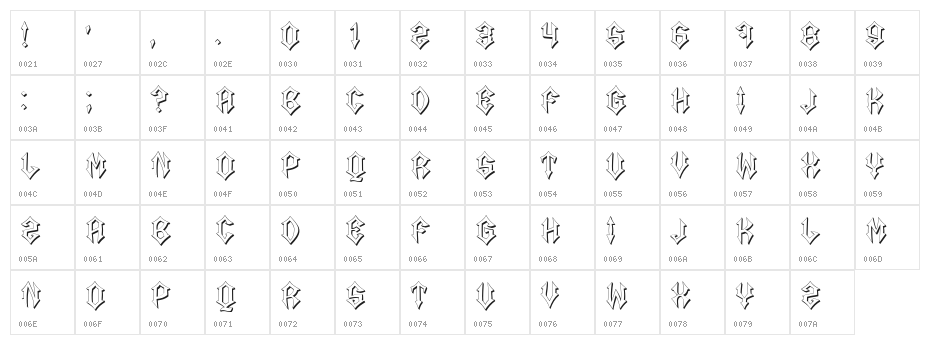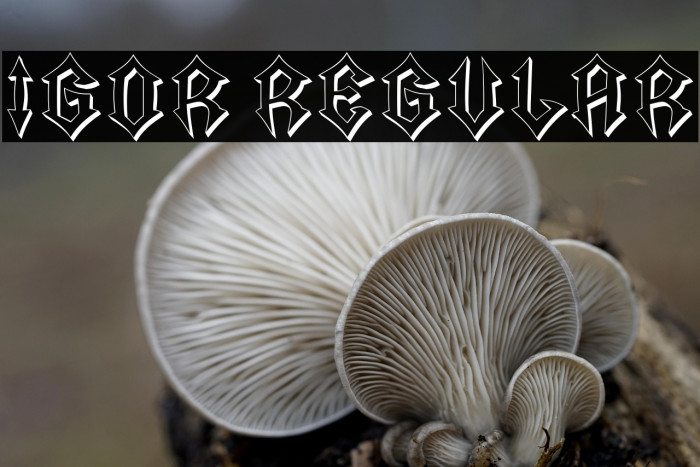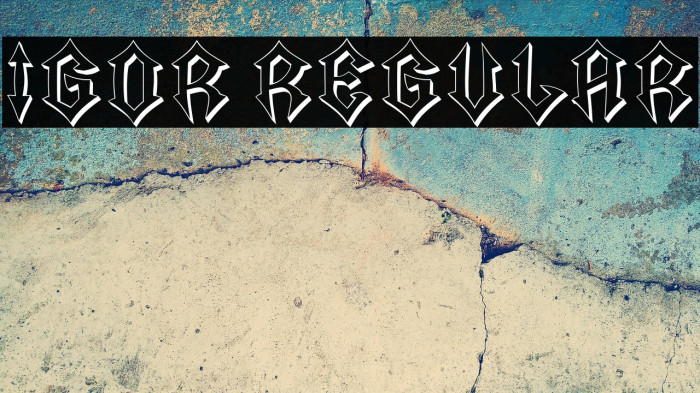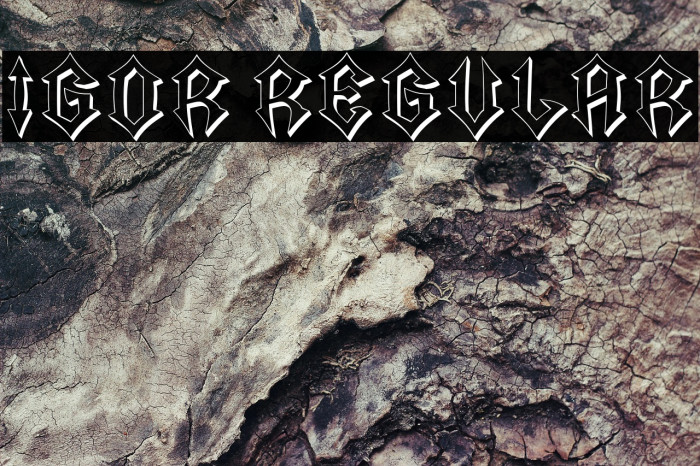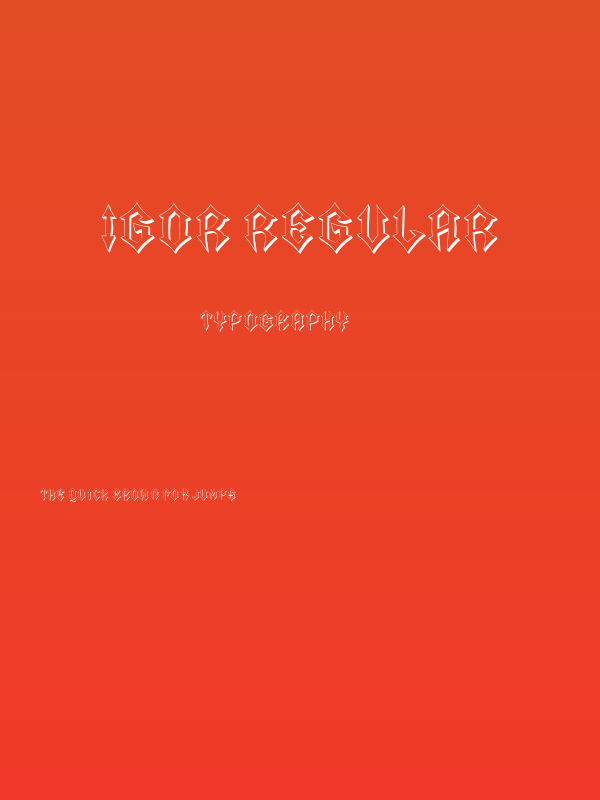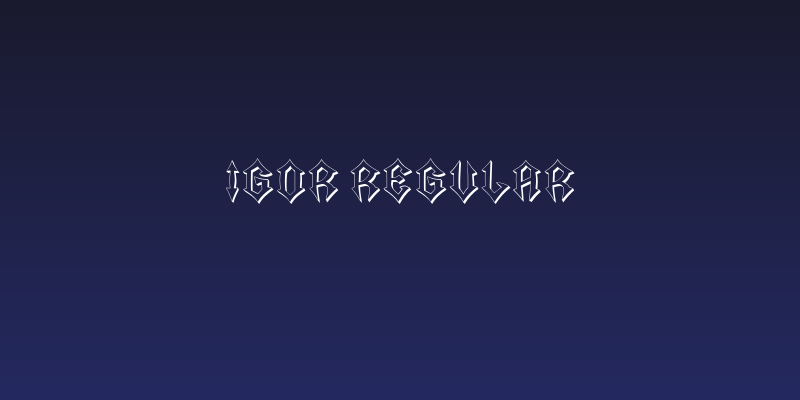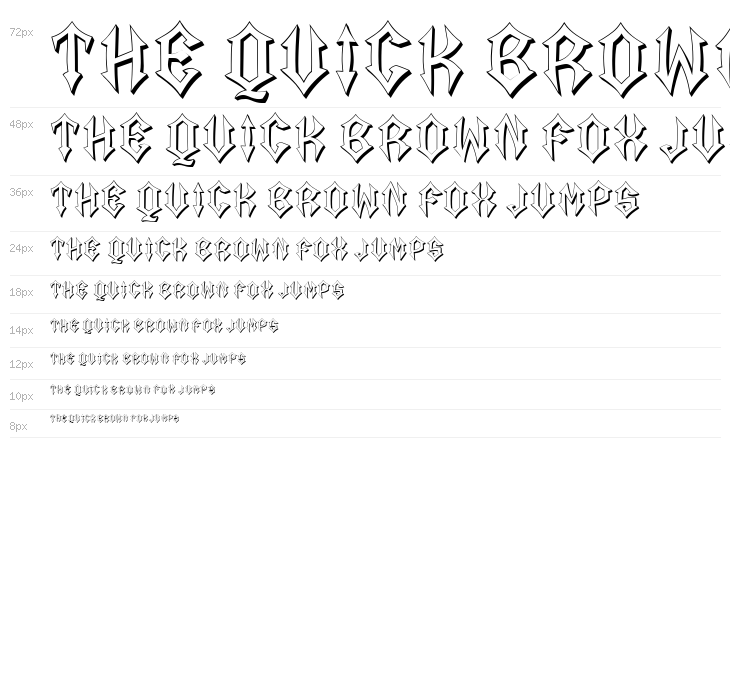
Igor Regular Font
| कंट्रास्ट | High |
| समग्र शैली | Gothic, Decorative |
| उपयोग का मामला | Headlines, Logos, Posters |
| सुझाए गए प्रोजेक्ट | Ideal for album covers, posters, tattoos, and branding that requires a bold, gothic aesthetic. |